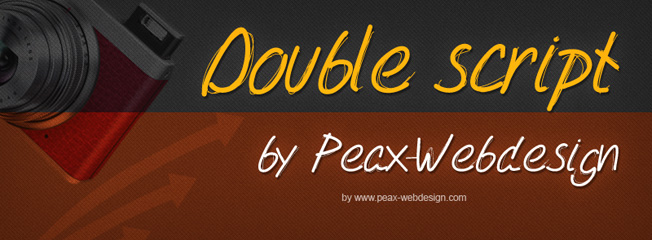
Malgré cette mise en scène un peu vintage, cette nouvelle typographie peut être adaptée à différents styles de graphisme. Je l'ai créée sur la base d'une police similaire (PW Simple Script) qui n'est pas encore en ligne, puis l'ai doublée de quelques filets - qui apportent un peu plus de dynamisme je trouve.